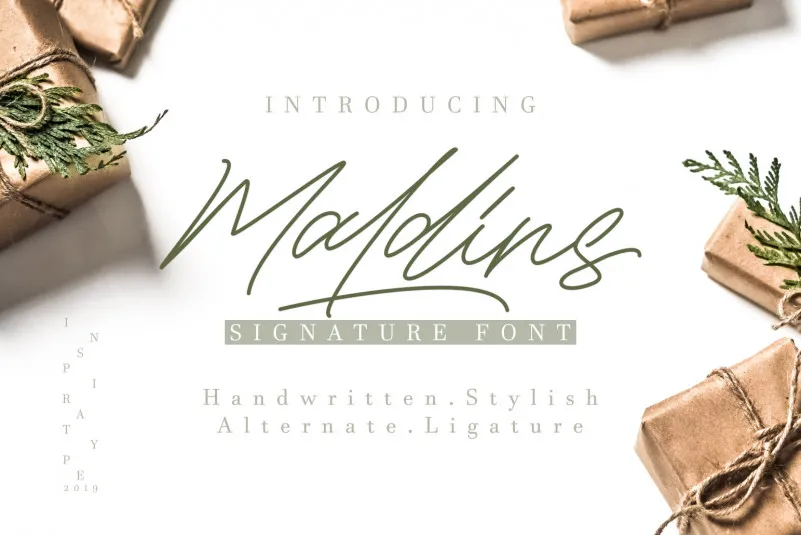
Maldins – Stylish Signature Font – Download Grátis
A fonte Maldins é uma escolha inigualável para aqueles que desejam adicionar um toque de estilo elegante a seus projetos digitais ou impressos. Inspirada nos tradicionais posters, essa elegante e artesanal tipografia foi criada à mão e traz com ela uma ampla variedade: desde as letras maiúsculas e minúsculas até números e pontuações, tudo é adaptável para oferecer um leque de variações únicas. O que torna Maldins ainda mais incomparável é a inclusão do OpenType alternativos, ligaturas comuns e até mesmo swashes – ou traços extra – para permitir que você personalize suas criações como nunca antes. A fonte é especialmente adequada para um vasto leque de aplicações: desde logotipos profissionais até as etiquetas em sua próxima embalagem criativa, do design de letras de carta à propaganda. Seja para decorar sua loja de roupas ou criar o próximo hit de camisetas digitais, a Maldins será um elemento irresistível e distintivo no seu trabalho. Se você busca uma fonte que seja tanto uma expressão pessoal quanto uma peça central do seu design, a Maldins é definitivamente uma escolha inegável. Não hesite em explorar todas as possibilidades criativas da sua próxima criação visual com esta poderosa fonte de escrita manuscrita.